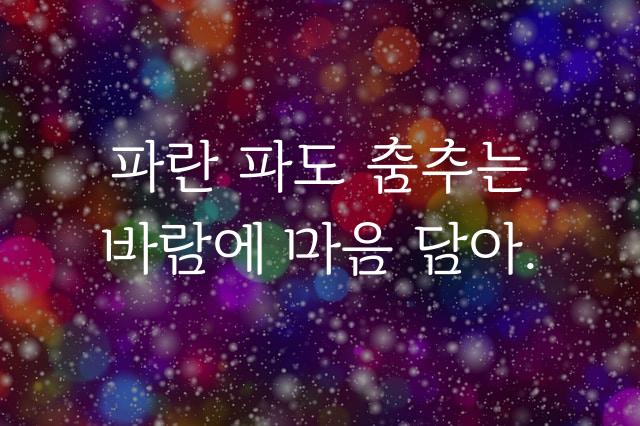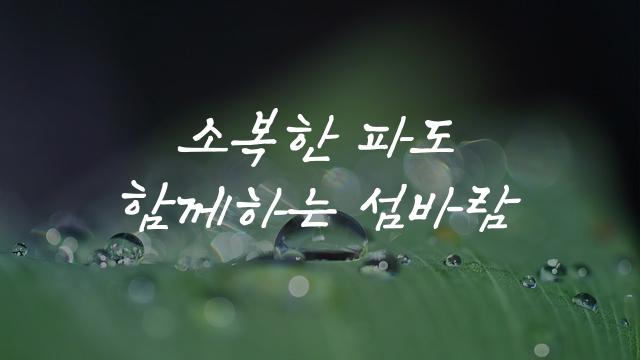
속초바다 돋움체는 속초시에서 제작한 제목용 및 장식체 폰트로, 둥근 고딕 스타일이 특징입니다. 이 폰트는 따뜻하고 부드러운 느낌을 전달하여 독자의 시선을 사로잡습니다.
속초바다 돋움체은(는)
별모양/패턴, 길고/크고, 기본 고딕, 복실복실, 부드러움, 감성적인, 장식 스타일, 둥근 스타일 계열의 생김새를 가지고 있으며
포스터, 소셜 미디어, 카페 메뉴 등에서 자주 활용되며, 효과적인 메시지 전달에 적합합니다.
이 폰트는 음식/식음료, 이벤트/웨딩, 관광/여행 분야에 잘 어울리며,
자연스러운, 편안한, 친근한 느낌을 담고 있는 것이 특징입니다.